Tổng hợp tên in mùa giải 23/24
Bộ font sẽ được Việt Hoá lại để chúng ta thoải mái đặt tên có dấu và những cái tên đúng như mong muốn của mình. Các bộ font chữ sẽ được chọn từ các bộ font từ các giải đấu lớn, CLB hàng đầu để mang đậm chất thể thao hơn cho từng chiếc áo được in.
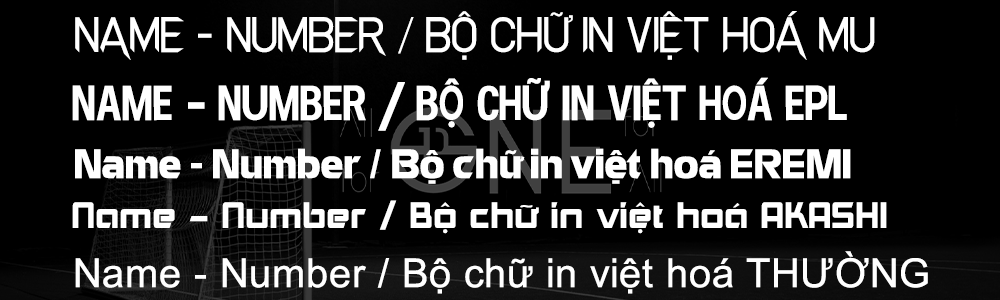
Tổng hợp Font số in mùa giải 23/24
Các bộ font số Sporter sẽ chia theo các bộ font Câu Lạc Bộ hoặc các Đội tuyển quốc gia. Hãy cùng xem qua và chọn một font số ưng ý nhất cùng Sporter nhé:
Bộ font số theo Câu Lạc Bộ:
Những số đấu thường được in trên các mẫu áo bóng đá Câu Lạc Bộ hàng đầu Châu Âu như Manchester United, Real Madrid, Barcelona, Bayern Munich,… và các giải đấu hấp dẫn nhất hành tinh.
Font Ngoại Hạng Anh 23/24
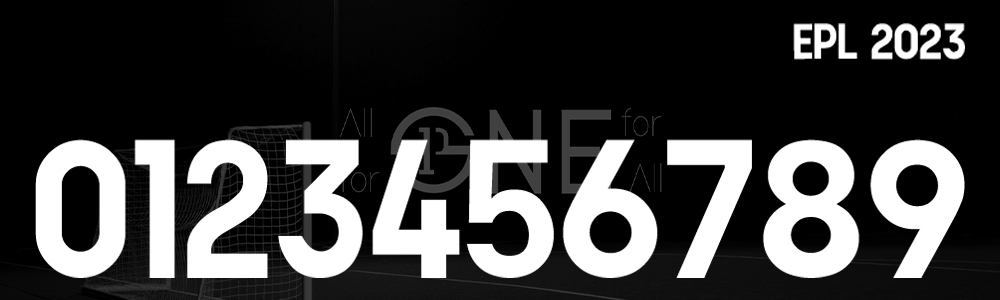
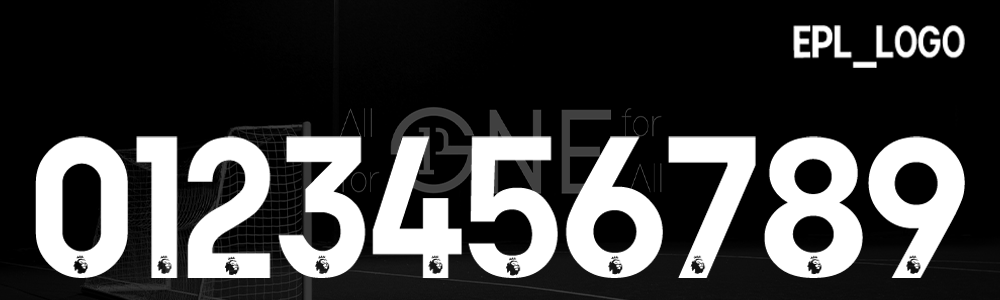
Font Ligue 1 (Giải Vô địch Pháp)
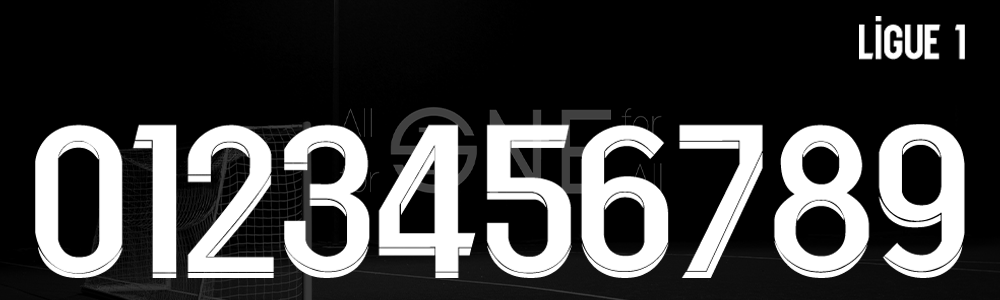
Font Al Nassr
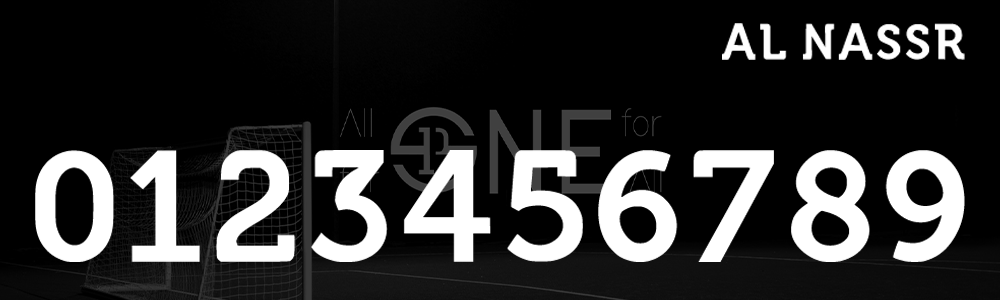
Font Arsenal
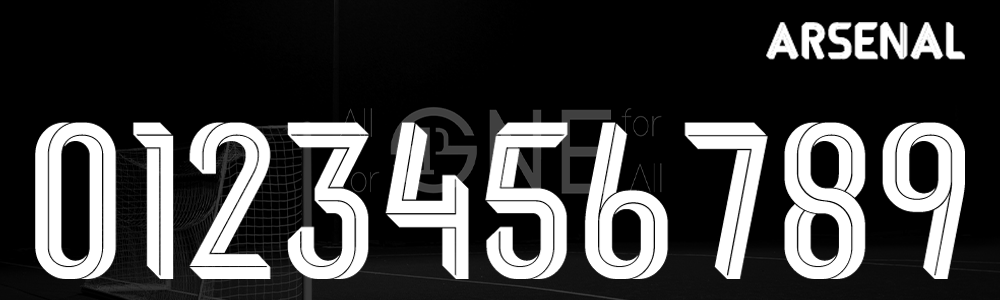
Font Barcelona
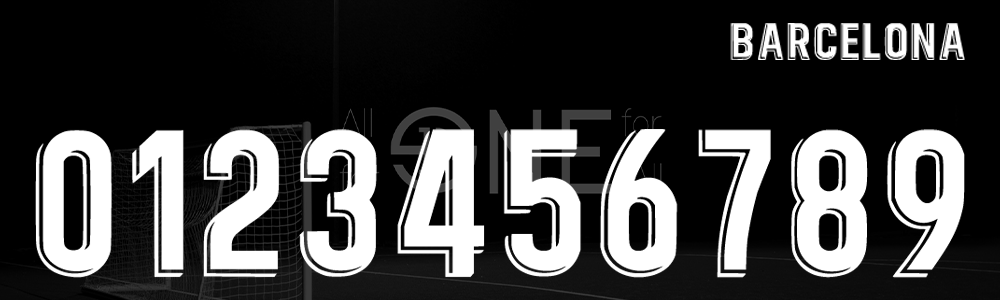
Font Bayern Munich
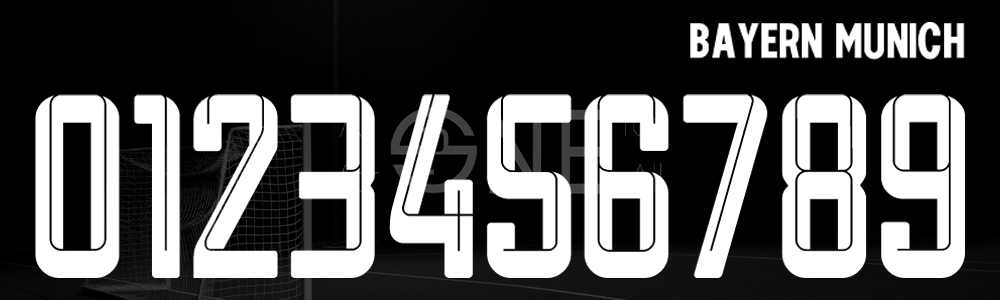
Font Manchester United
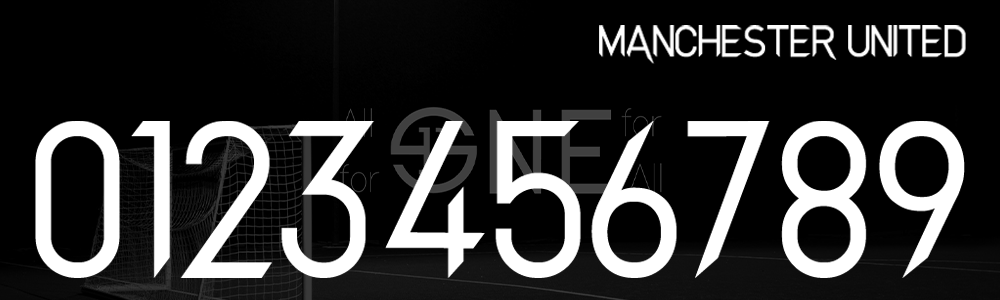
Font Real Madrid
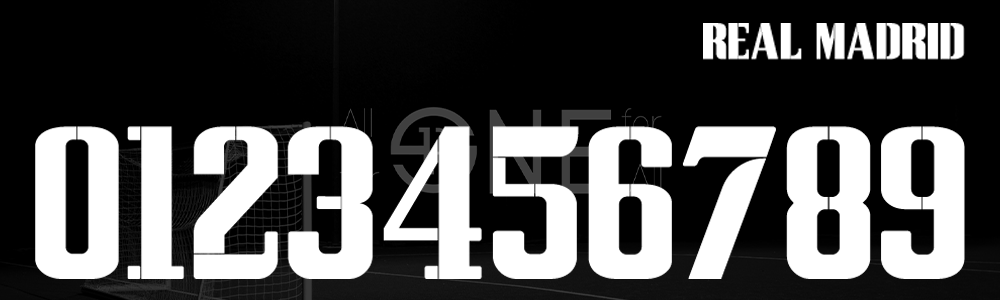
Bộ font số theo Đội tuyển quốc gia:
Các bộ số áo đấu của các đội tuyển quốc gia vừa tham gia giải World Cup 2022 hiện đã có tại Sporter.
Font Adidas
Font Brazil
Font Pháp
Font Hàn Quốc
Font Hà Lan
Font Bồ Đầu Nha
Font Mỹ
Ngoài ra, chúng ta còn có 1 bộ font dành cho các mẫu Áo bóng đá không logo:
Font Eremi
Lookbook hình ảnh thực tế các mẫu in thường – tên và số áo đấu